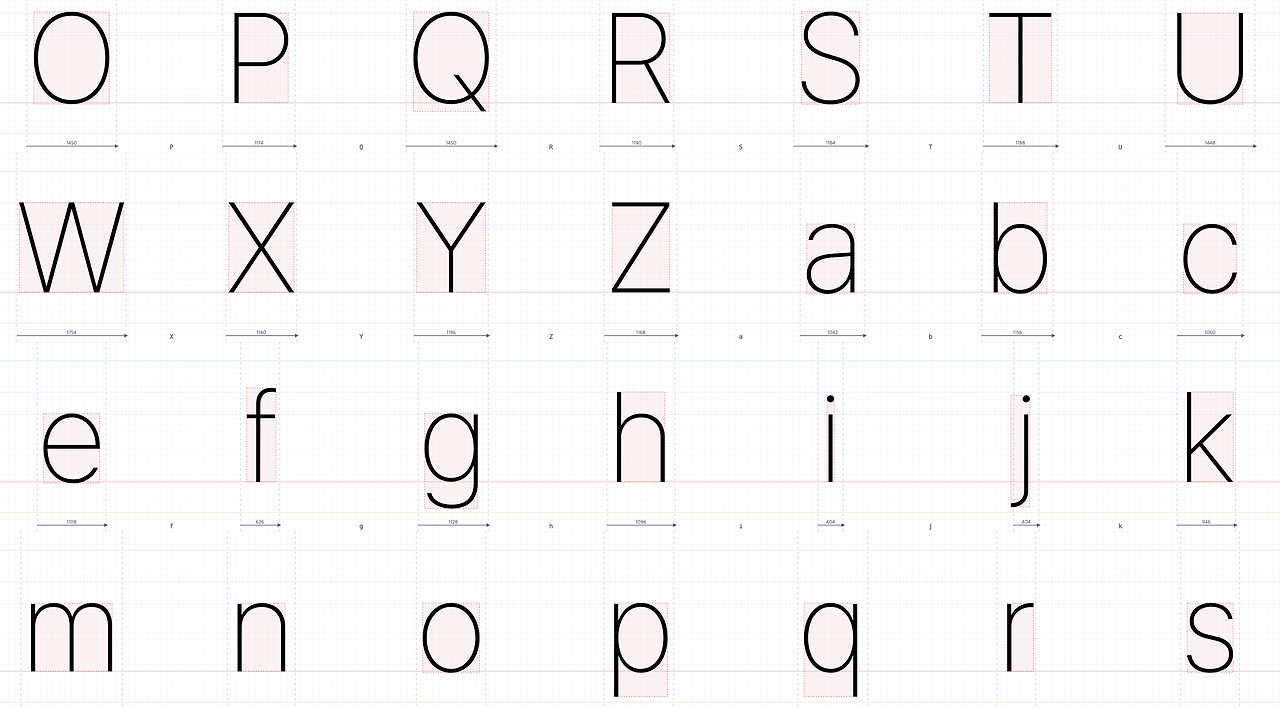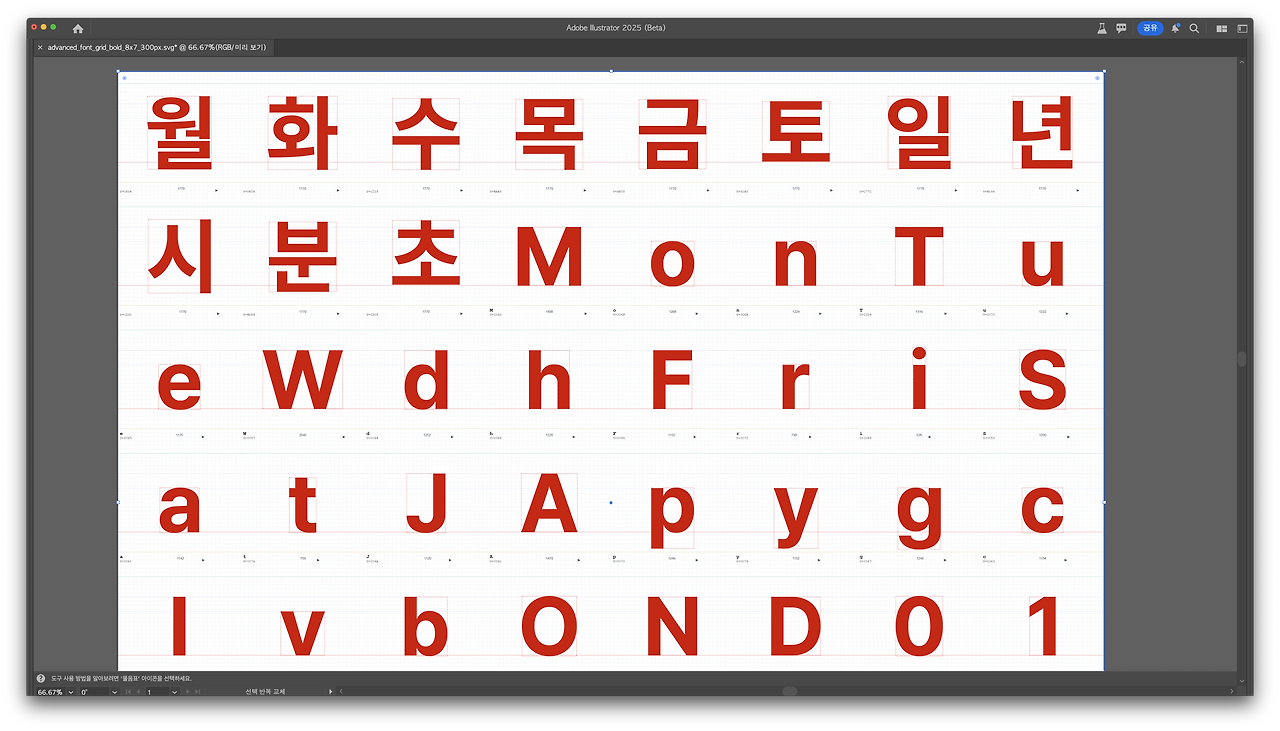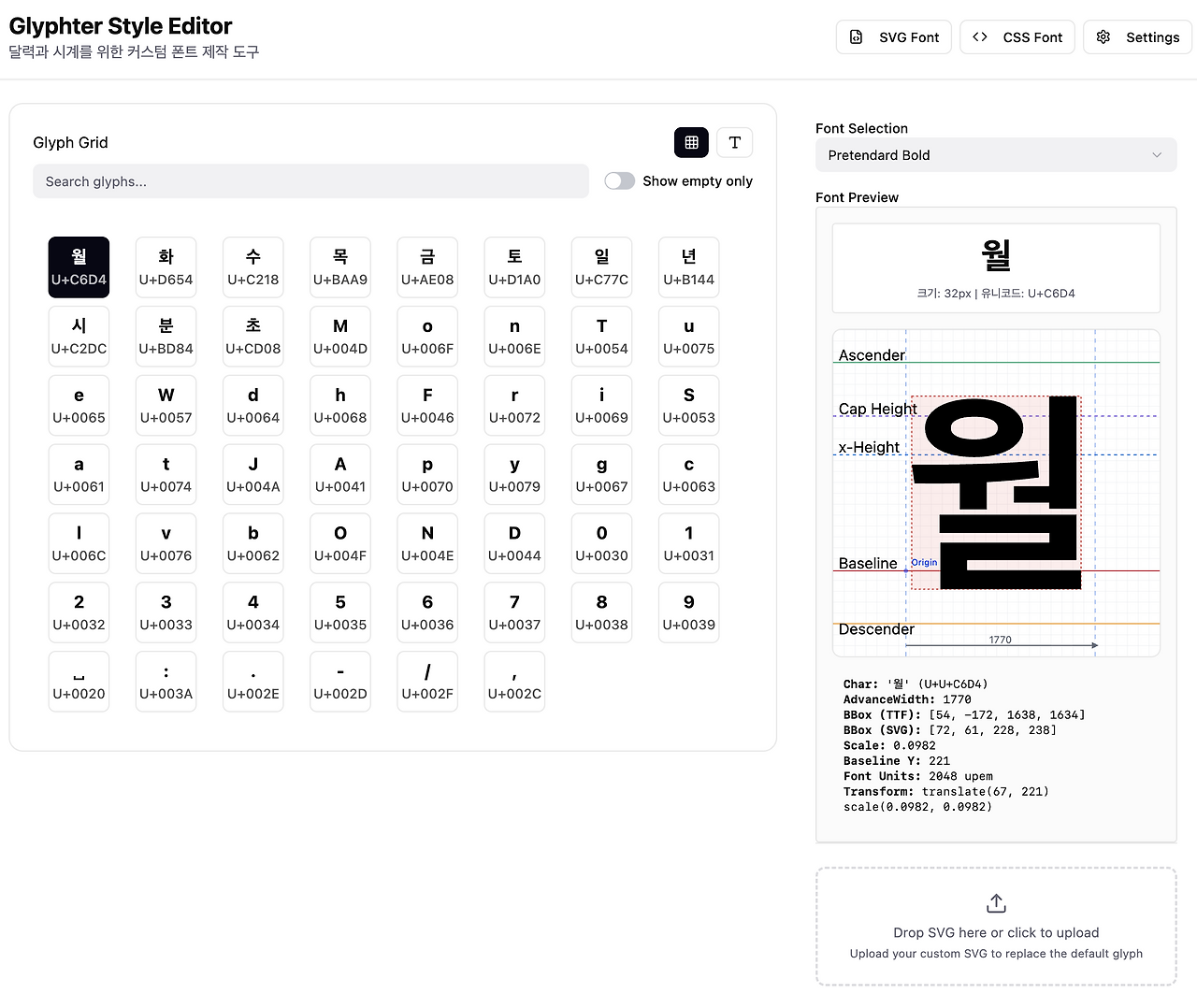
2026년 내가 만드는 손글씨 캘린더 시계 폰트
캘린더 폰트 작업이 거의 끝나가고 있어요! 한글날 전에 오픈할 수 있을 것 같아요. 두 가지 애플리케이션이 준비 중인데, 하나는 https://font.pics/ 처럼 손글씨로 폰트를 만드는 것이고, 다른 하나는 다운로드한 폰트를 격자대로 SVG로 디자인해서 캘린더와 시계 폰트를 만들 수 있는 애플리케이션이에요.
제가 디자인한 54개의 글자를 애니메이션 가이드까지 만들어서 캘린더와 시계에 사용할 수 있어요. 애플워치와 가로 위젯에서도 손글씨가 써지는 대로 디자인한 폰트가 똑같이 움직일 거예요.
결국에는 보여줘야 하니까, 2년간 쌓은 폰트 제작 기술과 휠 기반 캘린더 아이디어를 모두 결합하고 있어요.
일러스트레이터로 폰트별 데이터를 수정해서 업로드하면 폰트가 만들어집니다. 이제 달력시즌~